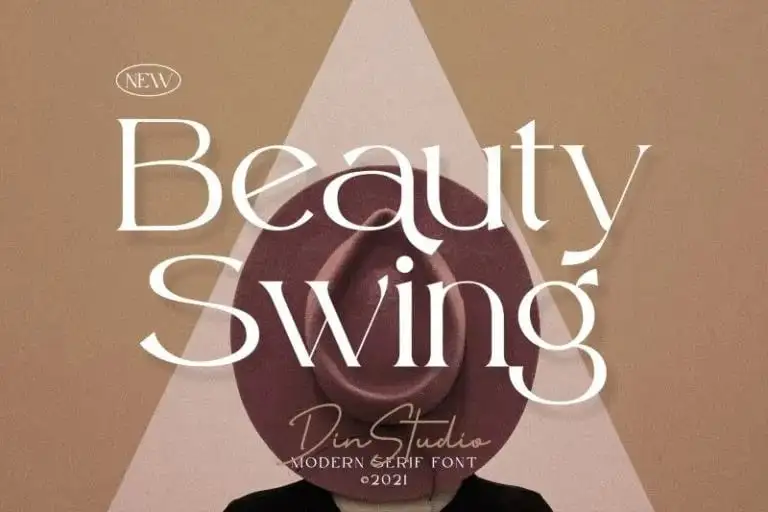
A Beauty Swing Serif Font é uma fonte serif elegante e sofisticada inspirada nos magazines de moda e nas marcas de perfumes. Ela captura a essência do estilo moderno através de sua rica ligatura, criada por Din Studio na plataforma 99designs. Perfeita para uso em várias aplicações, esta fonte é ideal para projetos de marca social, criação de moda e até mesmo como overlay de texto para imagens de fundo. Com um design fascinante e moderno, a Beauty Swing Serif é uma opção perfeita para destacar sua identidade visual e engajar seu público-alvo. É perfeitamente adaptável às diversas necessidades de conteúdo e projetos, tornando-a uma escolha sólida para qualquer aplicação gráfica que você possa imaginar. Não importa se for sobre estilos sociais, criações fashion ou simplesmente um overlay elegante em qualquer imagem de fundo – a Beauty Swing Serif terá o impacto desejado.